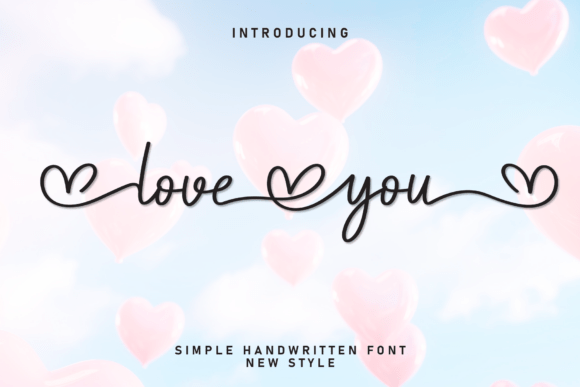
Love You
Love Youのような高品質の素材をお探しの場合、このプレミアムパッケージはクリエイティブなプロジェクトに素晴らしい選択です。
精密に作られたLove Youは、クリーンなベクター、滑らかなタイポグラフィ、そして安心のための商用ライセンスを提供します。
POD(オンデマンド印刷)製品、結婚式の招待状、またはソーシャルメディアのグラフィックを作成している場合でも、Love Youは理想的です。